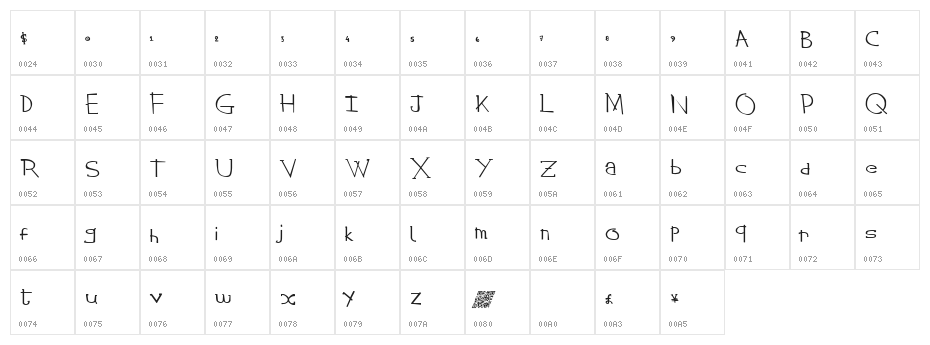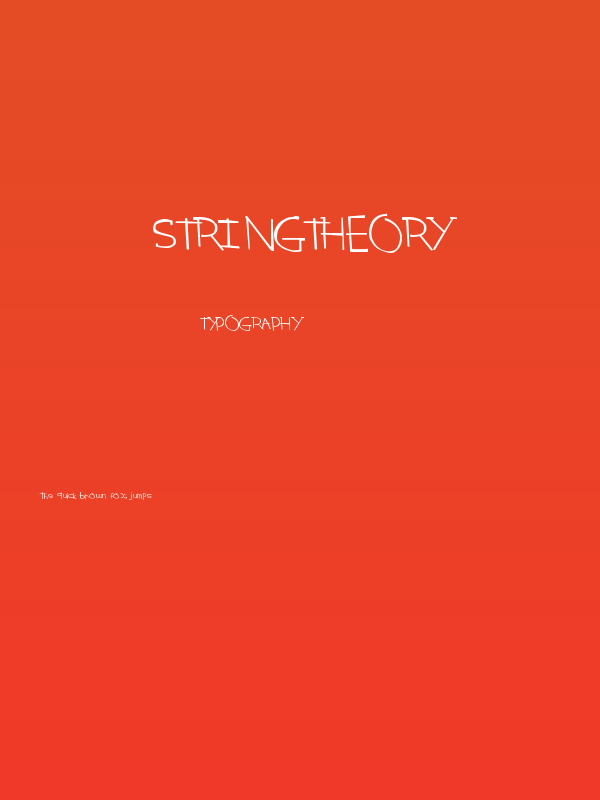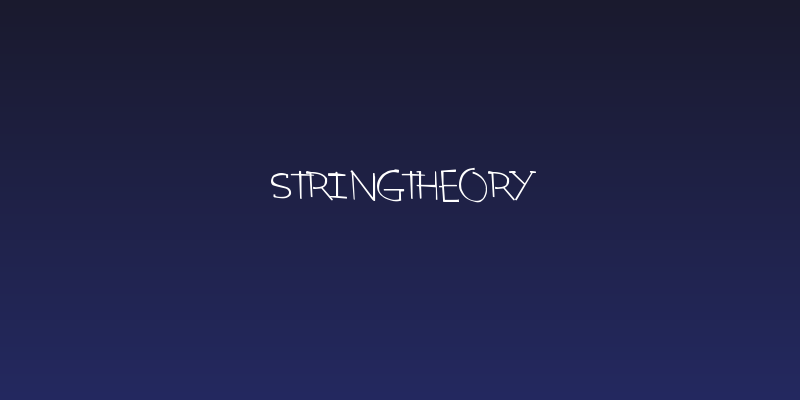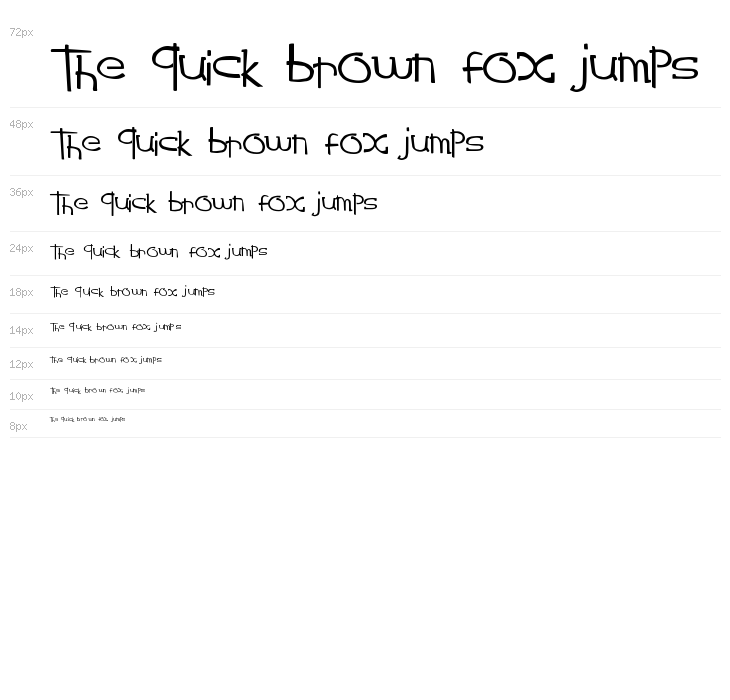
StringTheory Font
| 整体风格 | Whimsical, Artistic |
| 使用场景 | Headlines, Logos, Creative projects |
| 推荐项目 | Ideal for children's books, creative posters, artistic branding, and informal designs. |